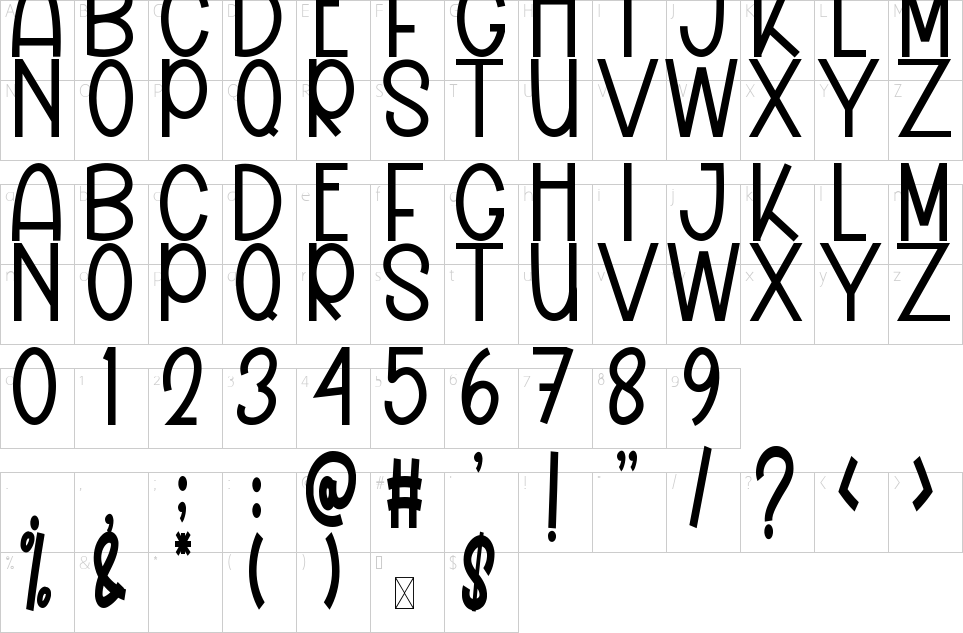
Girl Child Font – Fonte Grátis
Girl Child Font
A Girl Child font é uma opção elegante e feminina para quem busca estilizar seu texto com um toque delicado. Criada pela InermediaSTUDIO, a font foi projetada especificamente para aqueles que buscam uma fonte cuidadosa e amigável, especialmente adequada para aplicativos educacionais ou de promoção da igualdade de gênero. Ela é ideal para designers gráficos procurando adicionar um toque suave e feminino aos seus projetos, proporcionando uma excelente experiência visual que ressalta o conteúdo com delicadeza e simpatia. Com a Girl Child font, você pode enriquecer seu design com um detalhe que representa valores positivos e uma atenção especial para a importância da educação e dignidade de todas as crianças, independentemente do sexo. É uma escolha inspiradora para aqueles comprometidos com o uso criativo e educacional da linguagem visual.